Tổng hợp 5 font thiệp cưới Việt hóa đẹp
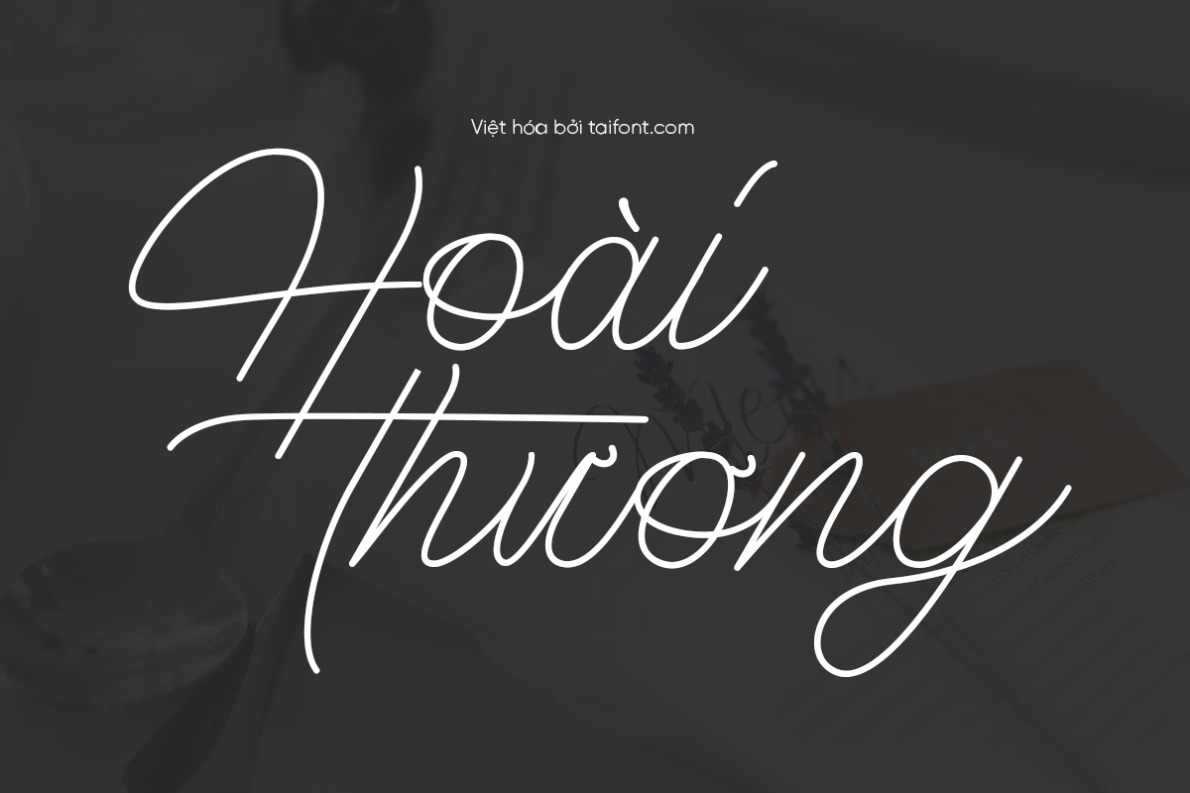
Tổng hợp 5 font thiệp cưới Việt hóa đẹp cho các thiết kế thiệp cưới, tạo nên thiệp cưới tuyệt đẹp cho cô dâu chú rể.
Top 1: Font Việt hóa TF Rainyday | Link tải
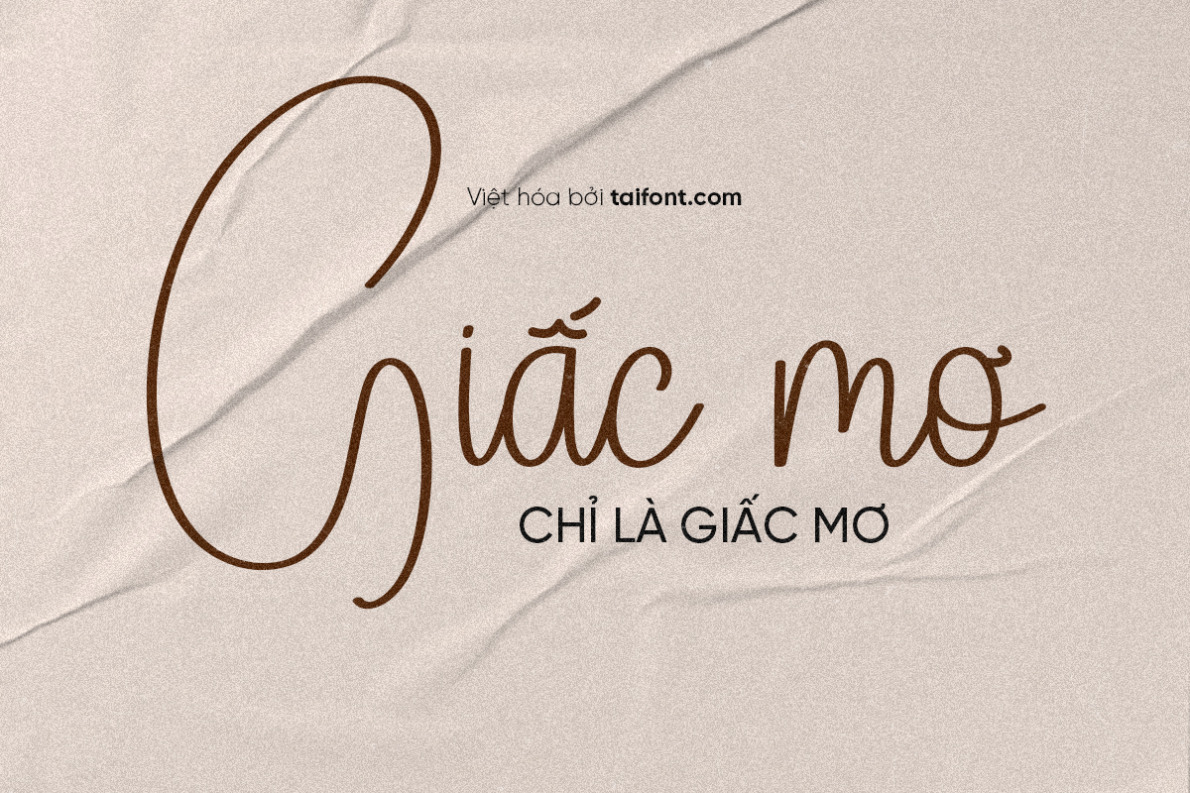
Font Việt hóa TF Rainyday có những đường nét uống lượt mượt mà. Font phù hợp với thiết kế thiệp cưới tinh tế
Top 2: Font Việt hóa TF Tulisan Signature | Link tải
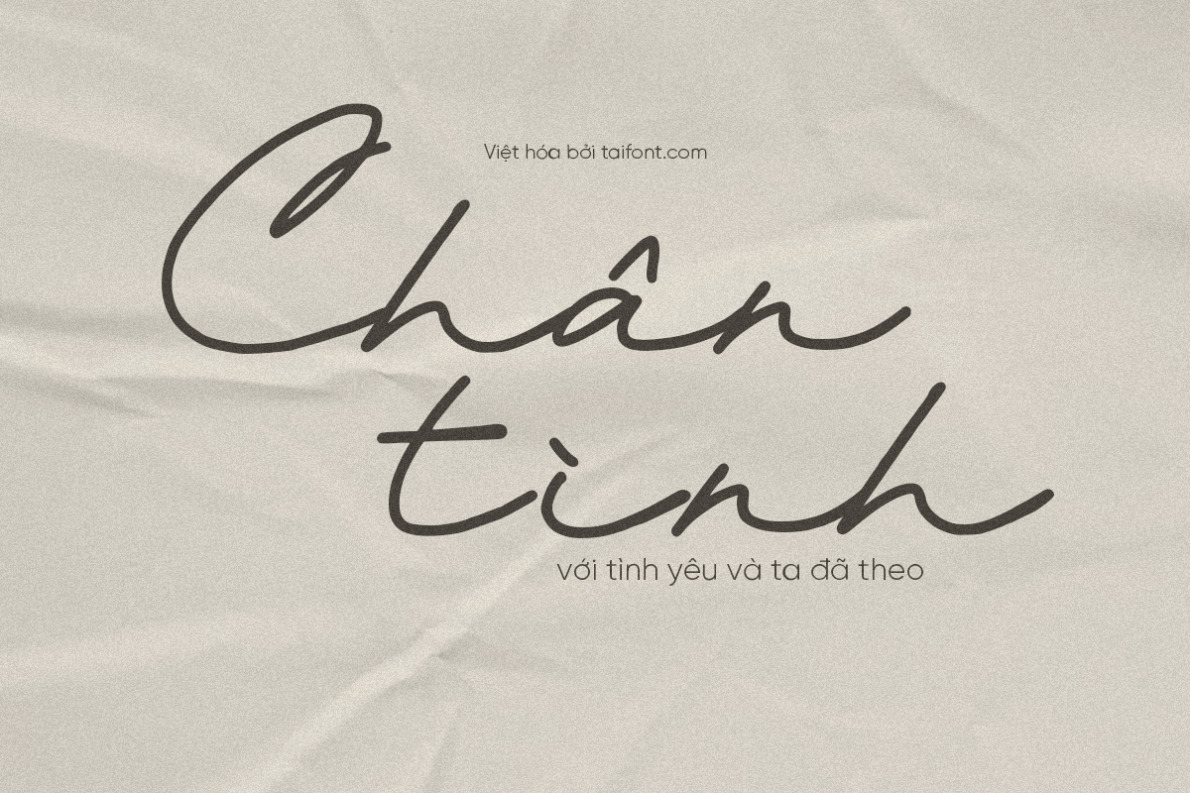
Font Việt hóa TF Tulisan Signature là font viết tay có nét đậm, phù hợp với thiết kế tiêu đề thiệp cưới thiệp mời.
Top 3: Font Việt hóa TF Halaline | Link tải
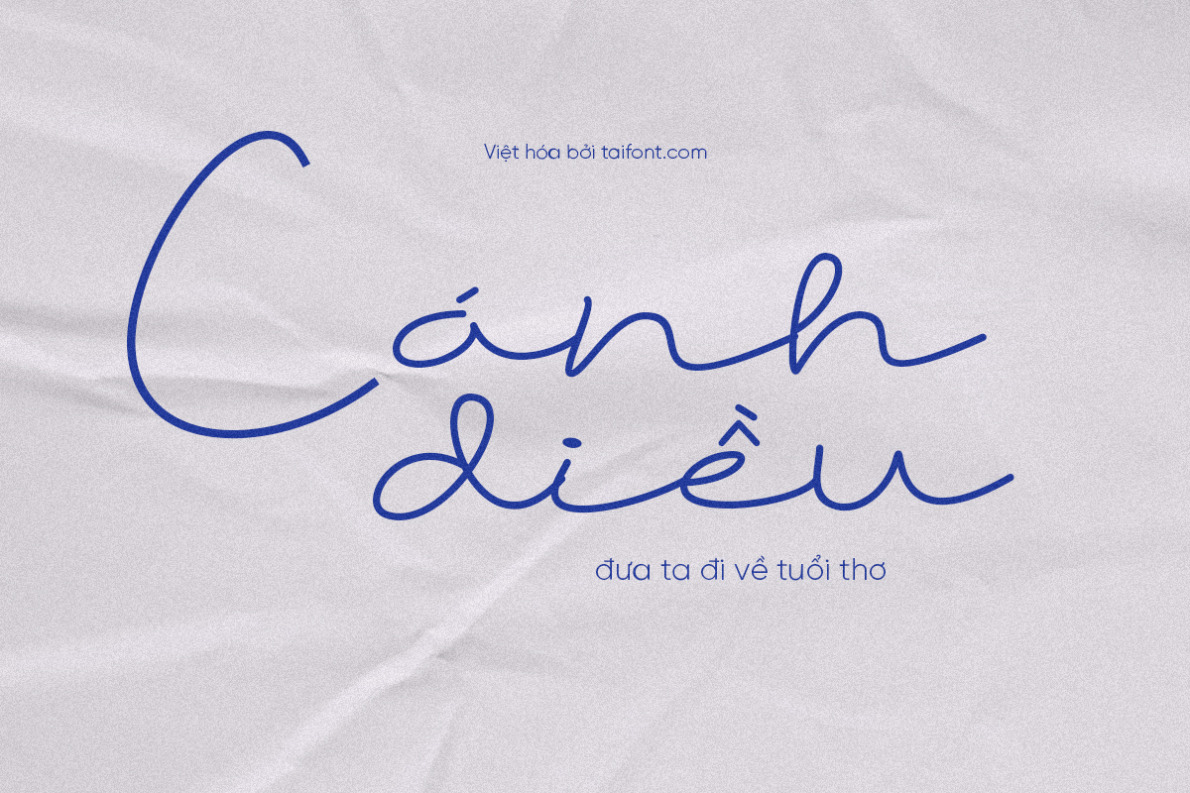
Font Việt hóa TF Halaline được thiết kế đầy sự tu của nét viết tay. Phù hợp cho các thiết kế chữ ký, thiệp mời, thiệp cưới
Top 4: Font Việt hóa TF Melfianita | Link tải
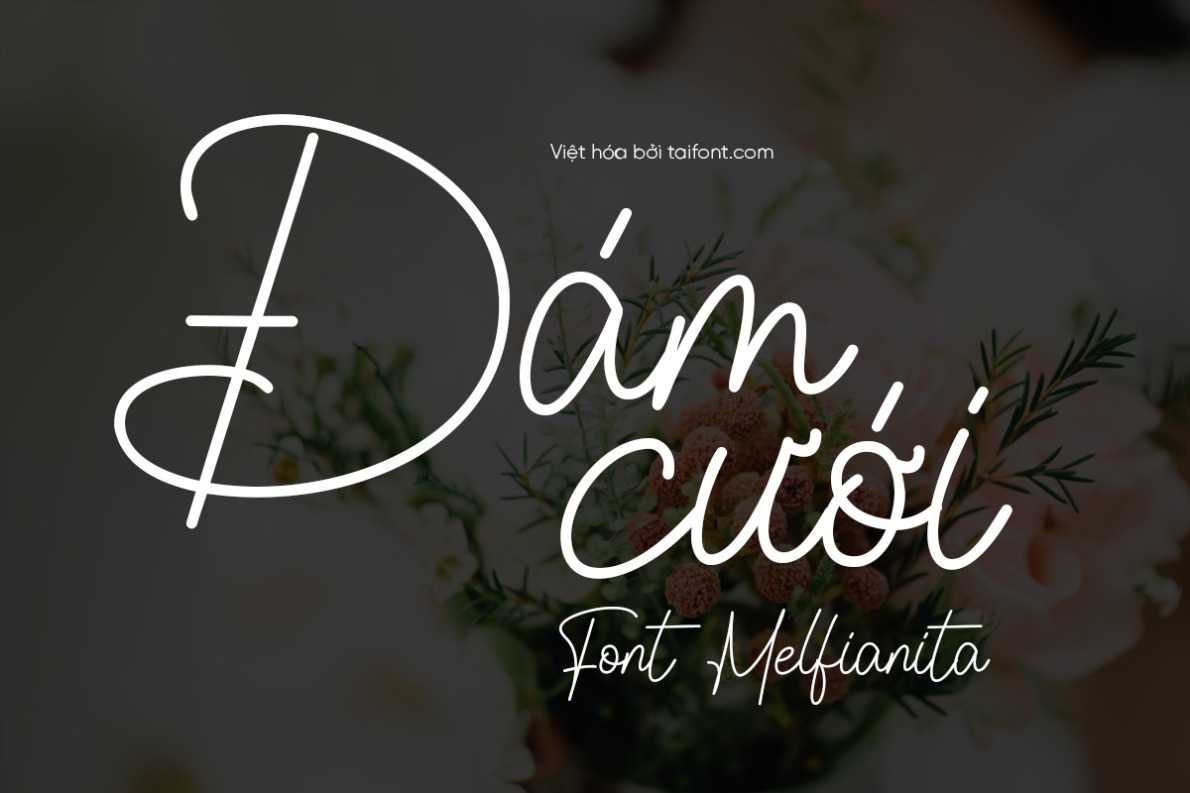
Font Việt hóa TF Melfianita là một font viết tay đẹp cho thiết kế thiệp cưới, thiệp mời.
Top 5: Font Việt hóa TF Nebuliqua Signature | Link tải
Font Việt hóa TF Nebuliqua Signature là font viết tay nét mảnh, phù hợp với thiết kế thiệp mời, thiệp cưới.